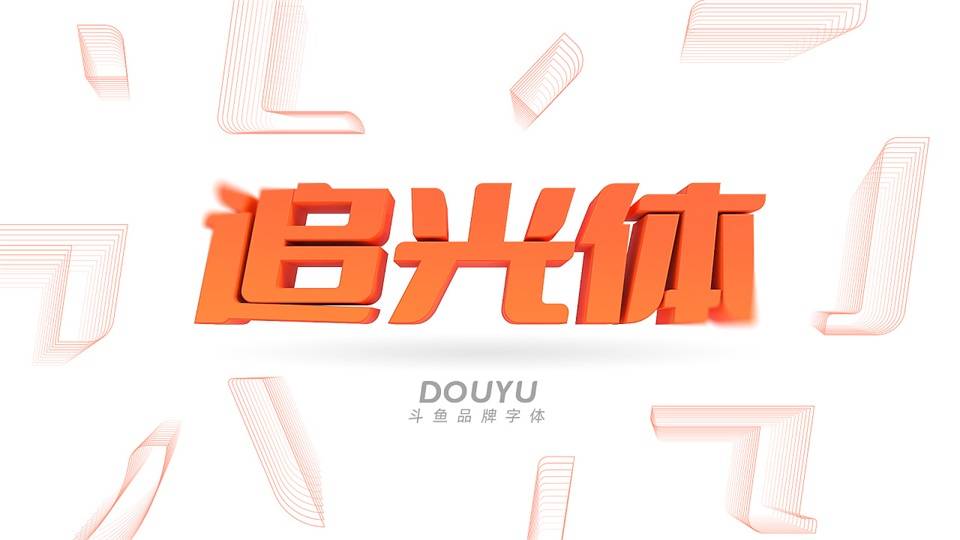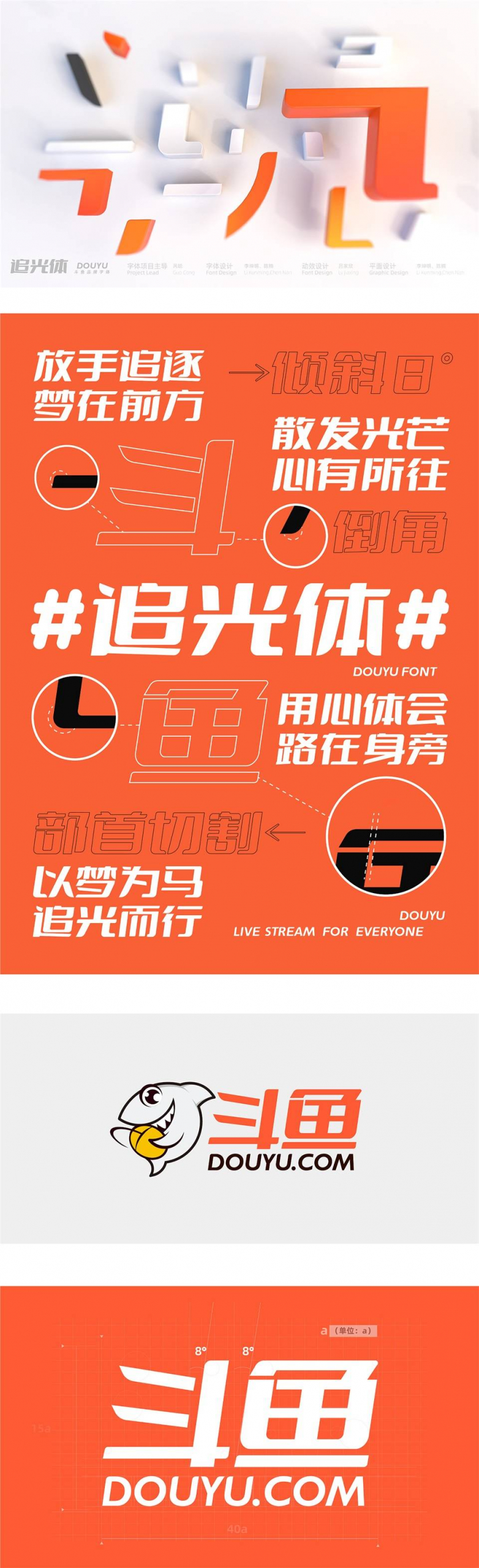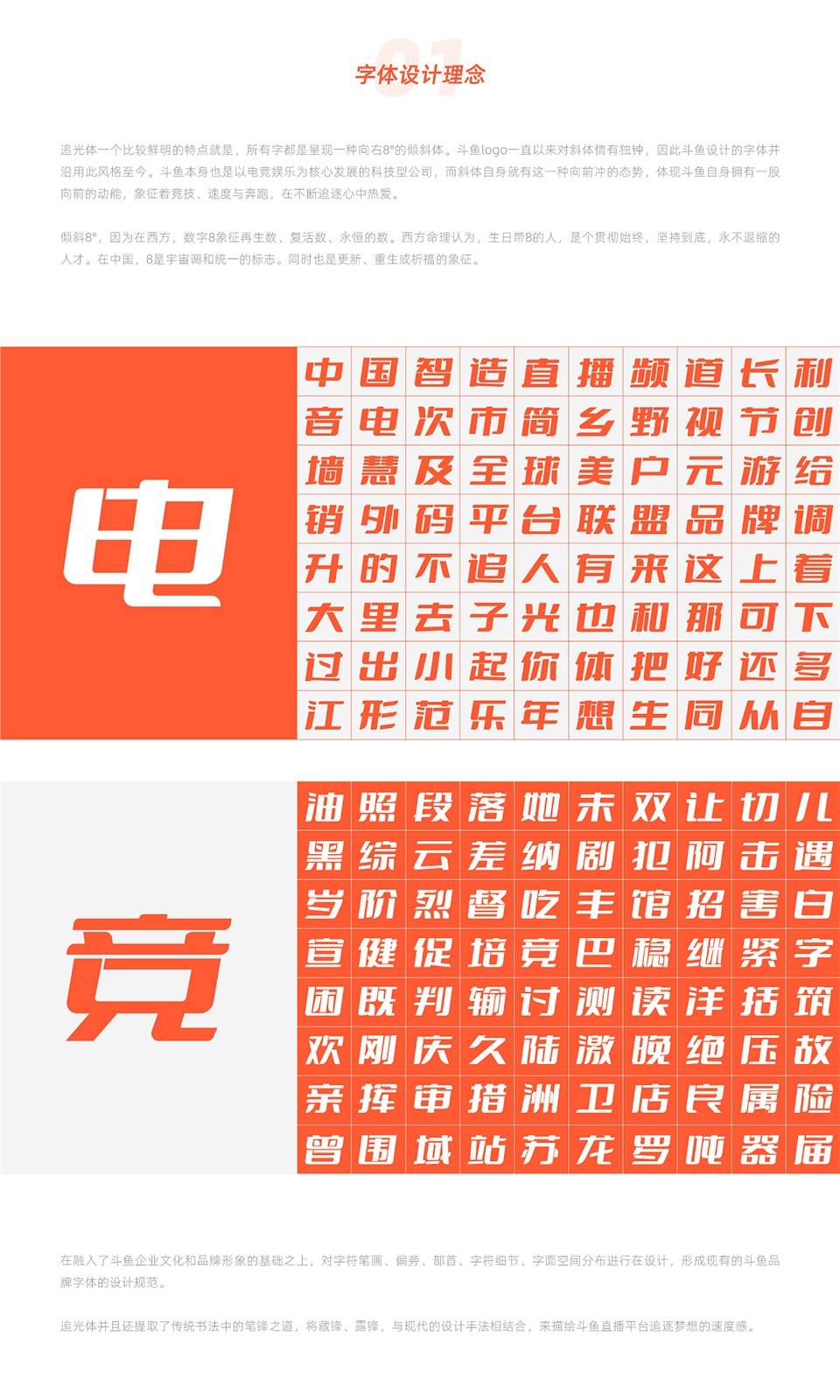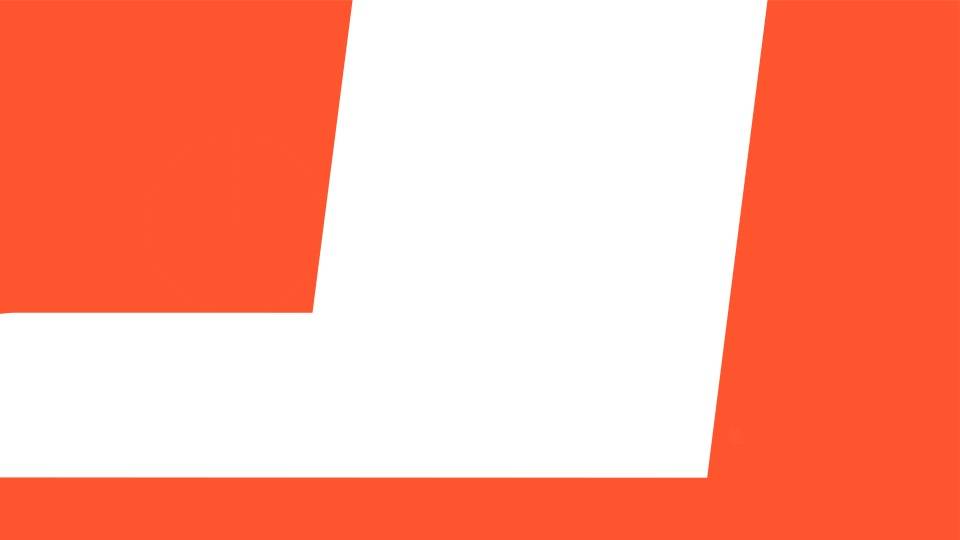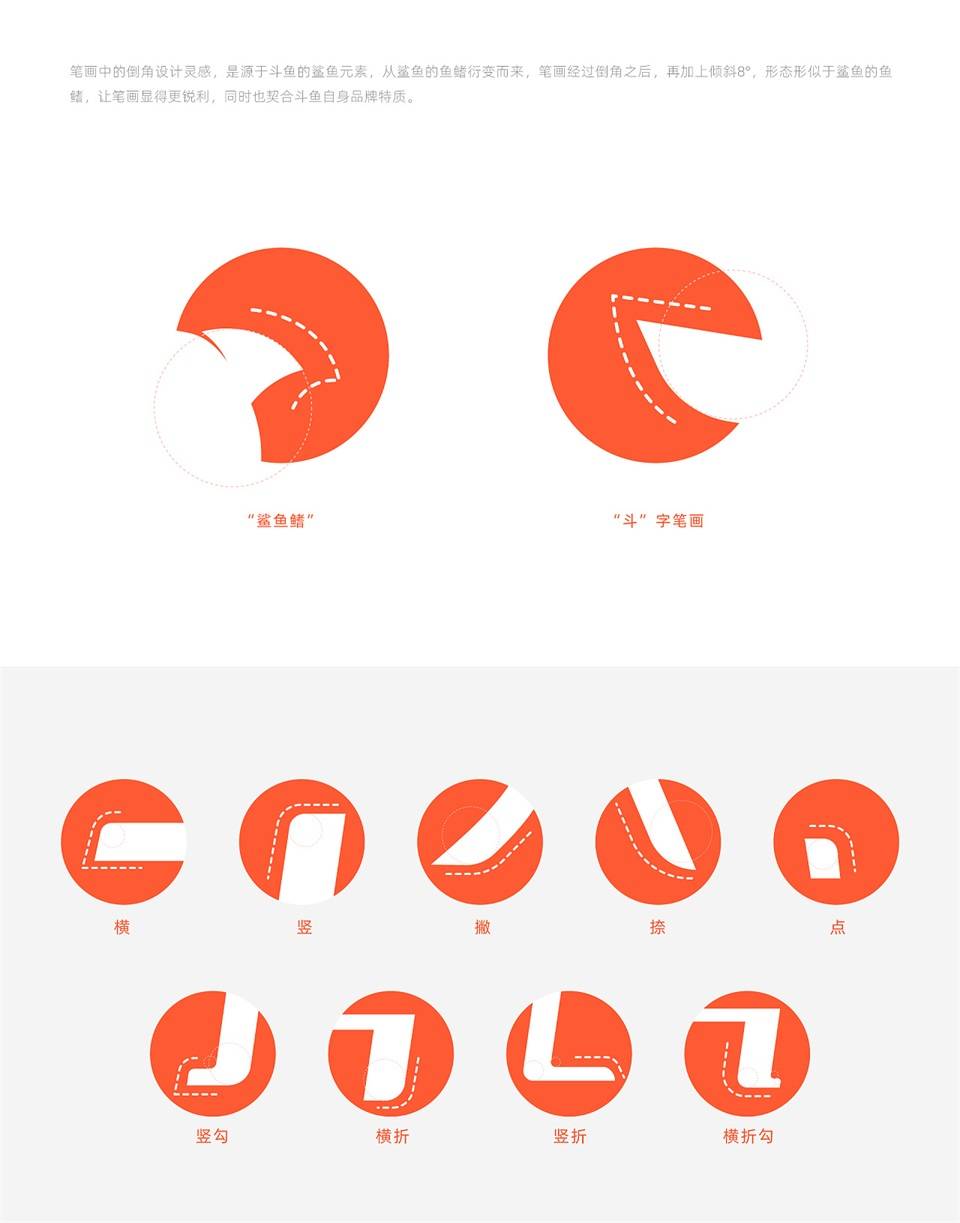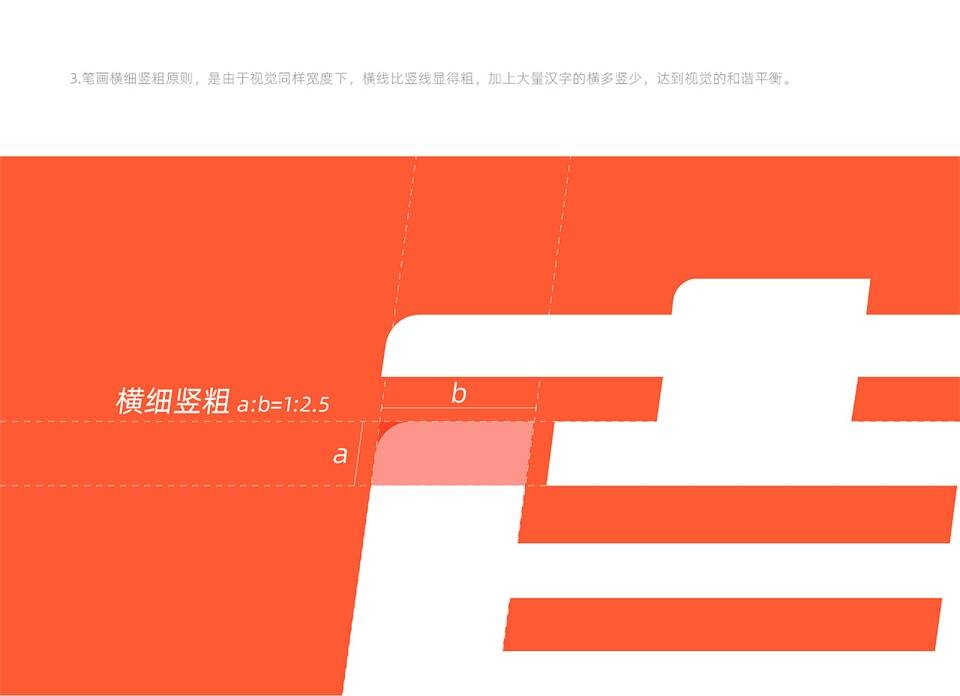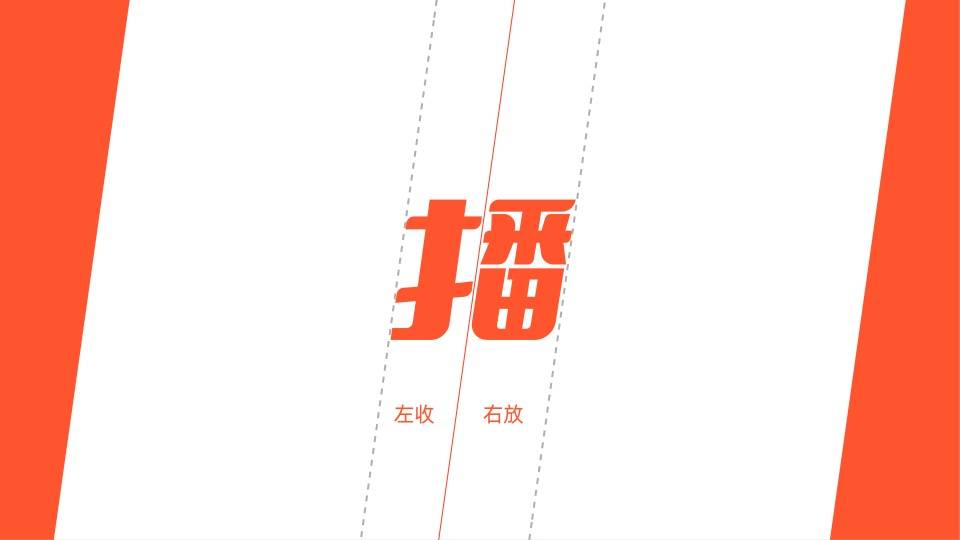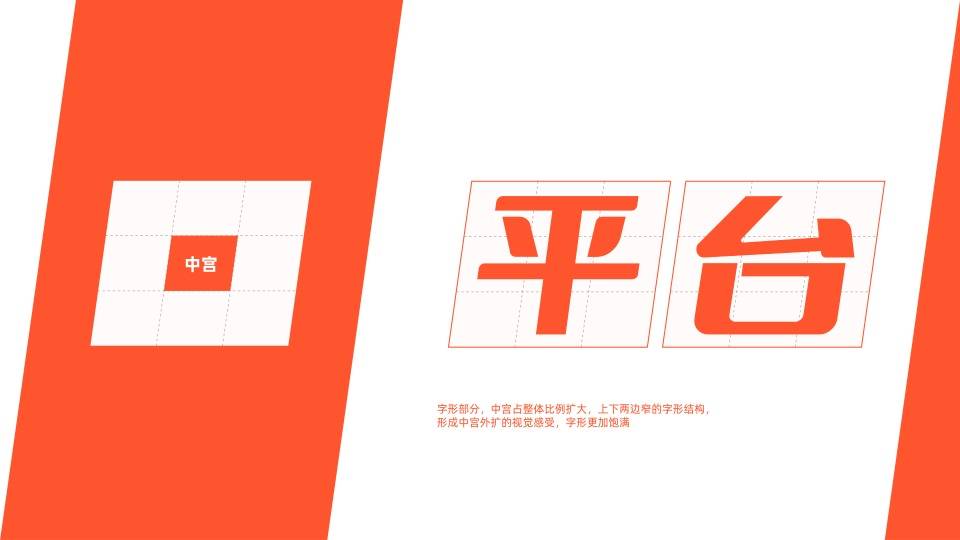
斗鱼追光体,是由斗鱼武汉研发部UED提供指导,品牌组设计成员主导设计的全新品牌字体。很多人会问,斗鱼为什么要设计自己的字库,我们并非心血来潮,作为一个在国内知名的直播平台公司,我们需要统一的字体来发声,来表现企业自身的风格,并且向外界传递我们自己的品牌特质。我们也想统一公司内所有的子品牌标志与各项目的宣传形象,在视觉上用同一种声音来凸显斗鱼。我们希望用户想到斗鱼公司时,是会联想到一个具有活力、上进,且具有娱乐性质的科技型公司。我们设计团队也是秉承着这些,来设计这套字体。
斗鱼追光体是符合GB2312简体中文编码字符标准的专属品牌字体。是拥有一种标准版字重,包含6763个中文字符,100个西文及数字符号。随着斗鱼品牌场景的日益丰富,斗鱼追光体能逐渐适配平台的各种场景。